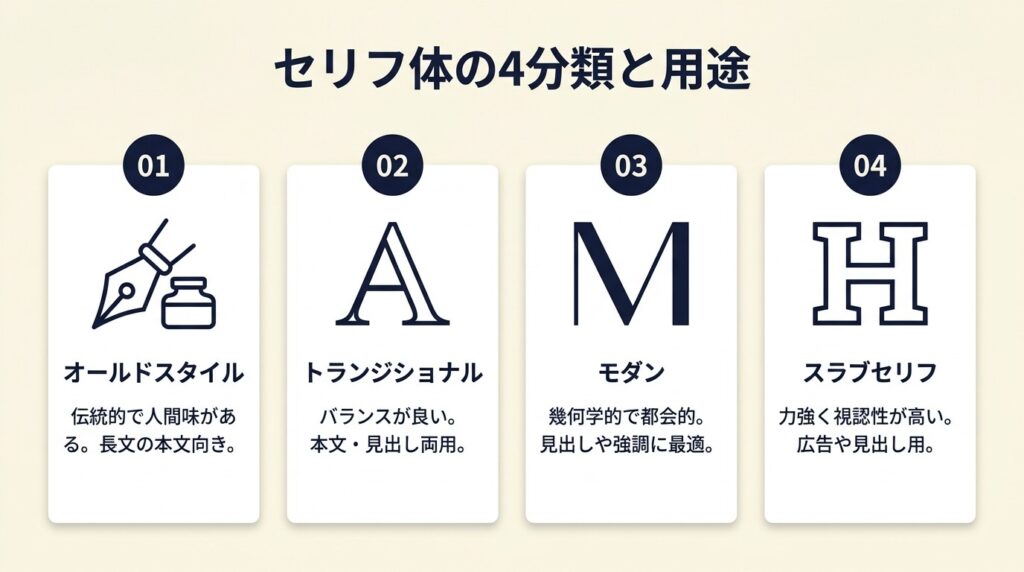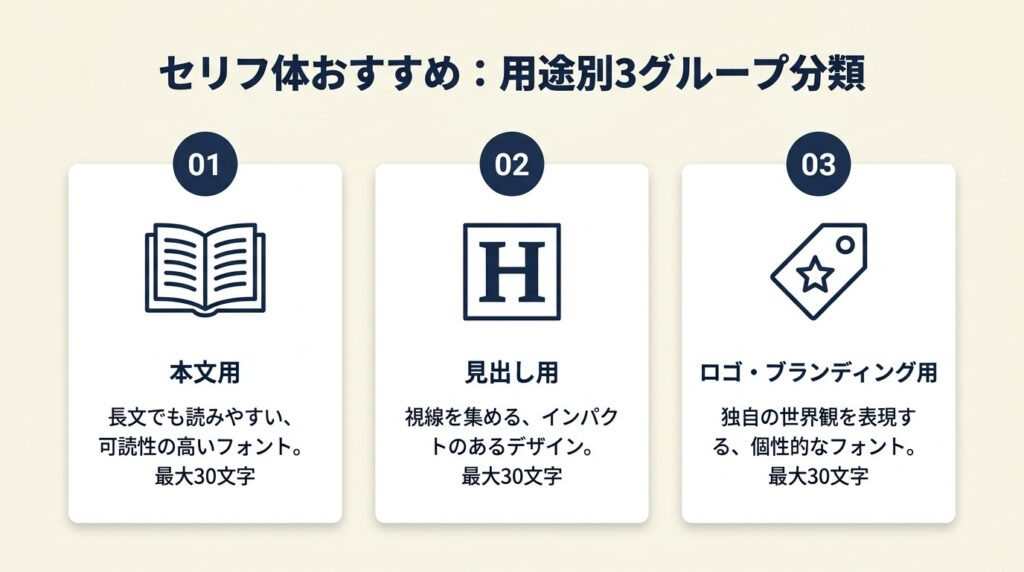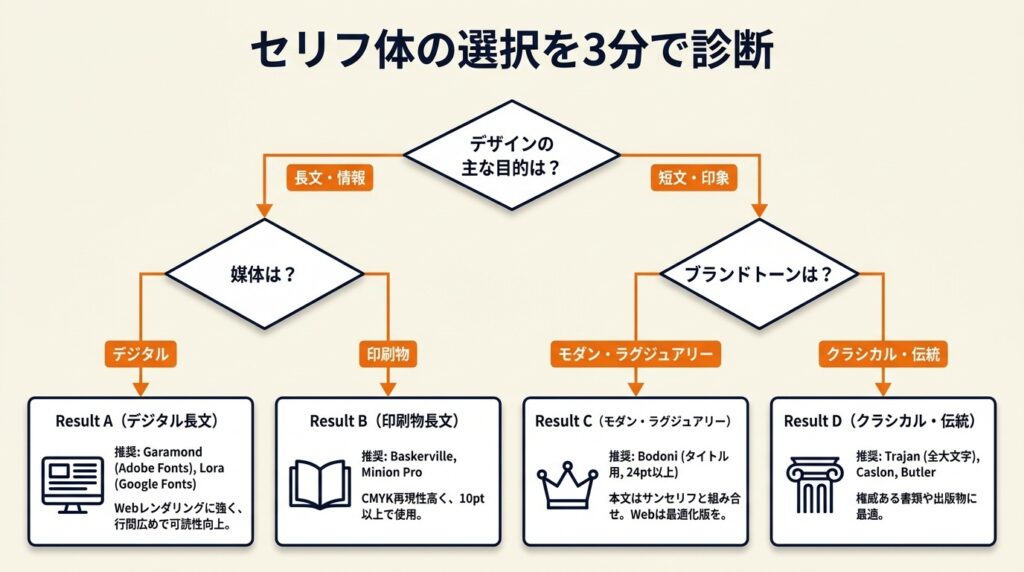
デザイナーが実務で使えるセリフ体は、用途別に選ぶと失敗がなく、見出しには10フォント中3選に絞れます。Adobe FontsとGoogle Fontsで無料商用利用できるものを中心に、本文・見出し・ロゴ別の選び方をこの記事で解説します。
本文用セリフ体はGaramondとBaskervilleの2択で9割の案件に対応できます。見出し・ロゴ用途ではBodoni・Trajan・Butlerが実務定番で、商用無料のものだけに絞っても選択肢は十分にあります。4種類の分類を理解するだけで、フォント選びに迷う時間を5分以内に短縮できます。
セリフ体の選択は「用途と印象の一致」が最優先です。見出しにはTrajanやBodoni、本文にはGaramondやBaskerville、モダン印象を出したい場合はスラブセリフのRockwellが定石です。初心者はGaramond一択から始め、次にBaskerville・Bodoniと段階的に習得すると迷いがなくなります。
セリフ体は4種類で用途が変わる
セリフ体は種類を理解すると選択肢が一気に絞られます。「なんとなく雰囲気が合いそう」でフォントを選んでいると、後工程で差し替えが発生しやすくなります。4分類を先に把握してから候補を絞るのが最速のアプローチです。
ブラケットセリフは長文可読性が最高
ブラケットセリフは、セリフ部分が滑らかなカーブで本体の線とつながっている書体です。GaramondやBaskervilleが代表例で、目が文字の流れを自然に追いやすい構造になっています。書籍・雑誌・Webの長文本文で最も多用されるのがこのタイプです。「読ませるデザイン」を作るなら、まずブラケットセリフを検討するのが最速の判断です。
ヘアラインセリフは高級感と繊細さを両立
ヘアラインセリフは、セリフ部分が水平方向に極細い線として表現された書体です。DidotやBodoniが該当し、縦の太線と横の極細線のコントラストが最大化されているため、ラグジュアリーブランドや高級誌での使用率が突出しています。ただし小サイズでは横線がつぶれやすく、12pt未満での使用は視認性が低下するため、見出しやロゴ専用と考えるのが正解です。
スラブセリフはモダンとクラシカルを両立
スラブセリフは、セリフ部分が角張った太い矩形形状の書体です。RockwellやUnit Slabが代表例で、太さのコントラストが低いため、アイキャッチやポスターで力強い印象を与えます。モダンデザインでありながら古典的な重厚感も持つため、テック系企業のブランディングから印刷物まで幅広く対応できます。「クラシカルすぎず、でも個性が欲しい」という状況で選ぶべきタイプです。
オールドスタイルは歴史的権威と読みやすさを両立
オールドスタイルは、15〜16世紀のヴェネチア・ローマン活版印刷に起源を持つ書体群です。Garamondがその代表で、縦横のストロークのコントラストが控えめで、長時間読んでも目が疲れにくい設計になっています。Times New Romanもこのカテゴリに分類され、新聞・学術誌・法律文書での採用実績が最も長い書体群です。権威性や信頼感を前面に出したいデザインで第一選択になります。
よくある質問
Q: セリフ体と明朝体は同じですか?
A: はい、同じ概念の別呼称です。セリフ体は欧文フォントの分類名で、日本語フォントでは同様の装飾を持つものを明朝体と呼びます。欧文デザインではセリフ体、和文デザインでは明朝体という用語が一般的です。
Q: サンセリフ体との使い分けはどう考えますか?
A: セリフ体は「伝統・権威・可読性」、サンセリフ体は「現代・清潔・視認性」と整理すると使い分けがしやすくなります。同一デザイン内でセリフ体を本文、サンセリフ体を見出しに使う組み合わせは実務でも多用されます。
セリフ体おすすめは用途で3グループに分類
用途で3グループに分けると選択肢が明確になります。定番フォントを調べると10種類以上出てきますが、「本文用」「見出し用」「ロゴ・ブランディング用」の3軸で整理すると候補を一気に絞り込めます。
見出し用セリフ体は3選が実務定番
見出し用に最も多用されるセリフ体はTrajan、Bodoni、Didotの3つです。
TrajanはAdobe Systemsのキャロル・トゥオンブリーが1989年にデザインした書体で、大文字のみのキャピタル設計を持ち、映画タイトルやポスターへの採用実績が豊富です。シャープな彫刻的フォルムが視線を集め、権威あるタイトルデザインに適しています。Bodoniは縦横ストロークの最大コントラストが特徴で、ファッション誌の表紙での採用率が高く、モダンラグジュアリーの代名詞的存在です。DidotもBodoniと同様のモダンセリフ系ですが、よりスタイリッシュで細身の印象を与えます。いずれも小サイズでの使用は非推奨で、24pt以上での使用が前提です。無料英語フォントを3ステップで即使える方法でも解説しているように、フォントの種類と用途の対応を最初に整理することが、選択ミスを防ぐ最短ルートです。
本文用セリフ体は可読性で2選に絞れる
長文本文で最も信頼性が高いのはGaramondとBaskervilleです。
Garamondは16世紀のフランス活字師クロード・ガラモン(Claude Garamond)の書体を原典とし、現在Adobe Fontsで無料商用利用が可能です。字間のリズムが均一で長時間読んでも疲れにくく、書籍・Webの本文フォントとして選ばれ続けています。デザイナーがお気に入り欧文フォントを解説した記事では「セリフ体からは王道のGaramond、古典的でモダンなBaskervilleをご紹介。個性が強めなものを好むデザイナー視点。」と紹介されています。
BaskervilleはGaramondより縦横のコントラストがやや強く、学術的・フォーマルな印象が加わります。18世紀イギリスの活版印刷業者ジョン・バスカーヴィル(John Baskerville)の設計を受け継いだ書体で、現代のスクリーン表示にも十分対応しています。Garamondで少し軽すぎると感じた案件でBaskervilleに変えると重厚感がちょうど整うケースが多いです。
ロゴ・ブランディング用は個性と汎用性で選ぶ
ロゴ・ブランディング用途ではButlerとMinion Proが実績豊富です。ButlerはFabian De Smet氏が設計したフリーフォントで複数ウェイト展開があり、骨格がしっかりしており小サイズでも視認性を保ちます。Minion ProはAdobe FontsでAdobe CC契約者が無料で使えるフォントで、豊富なウェイトと幅のバリエーションから微細なブランドトーン調整が可能です。ロゴ制作で1つ選ぶならMinion Proが最初の候補になります。日本語フォント無料おすすめ12選でも触れているように、ウェイトバリエーションの豊富さはフォント選びの重要な判断基準のひとつです。
よくある質問
Q: Times New Romanは商用利用できますか?
A: WindowsおよびmacOSにプリインストールされているTimes New Romanは、OSにバンドルされたライセンスの範囲内でのみ使用可能です。Web埋め込みや印刷物の商業利用では、Adobe FontsのTimes New Roman互換フォントや、完全商用フリーのIM Fell Englishなどを使用してください。
Q: Google Fontsで使えるセリフ体はありますか?
A: はい、あります。Google FontsにはLora、Merriweather、Playfair Displayなど複数の高品質なセリフ体フォントがあります。いずれも無料で商用利用可能で、Webフォントとして直接埋め込むことも可能です。
セリフ体の選択を3分で診断
以下の質問で用途に合うフォントタイプが3分で絞り込めます。Q1から順に答えてください。
Q1: デザインの主な目的はどちらですか?
長文・情報を読ませる場合はQ2へ、短文・ブランド印象を伝える場合はQ3へ進んでください。
Q2: 媒体はデジタル(Web・アプリ)ですか、印刷物ですか?
デジタルの場合は**Result Aへ、印刷物の場合はResult B**へ進んでください。
Q3: ブランドトーンはどちらに近いですか?
モダン・ラグジュアリーの場合は**
Result Cへ、クラシカル・伝統の場合はResult D**へ進んでください。
**
Result A(デジタル長文)**: Garamond(Adobe Fonts無料)を12pt以上で使用してください。WebフォントとしてGoogle FontsのLoraも代替可能です。GaramondはWebレンダリングでも字間の均一性が高く、画面読了率が維持しやすいフォントです。行間は文字サイズの1.7〜2.0倍に設定することで可読性が最大化されます。
**
Result B(印刷物長文)**: Baskerville(Adobe Fonts無料)を本文10pt以上で使用してください。版面が狭い場合はMinion Proでウェイトを細調整できます。BaskervilleはCMYK印刷での再現性が高く、インクのにじみが出ても字形の判別がしやすい設計です。10pt以下ではセリフ部分がつぶれるため使用しないでください。
**
Result C(モダン・ラグジュアリー)**: Bodoniをタイトルに使用し、本文はサンセリフ体(Helveticaなど)と組み合わせてください。24pt以上を厳守します。Bodoniの縦横コントラストは印刷時に最大限発揮されます。スクリーン表示では細い横線がアンチエイリアスで劣化するため、Webのみの媒体ではBodoni Moda等のスクリーン最適化版を選んでください。
Q: 日本語と欧文セリフ体を組み合わせる方法を教えてください。
A: 欧文セリフ体と日本語明朝体を組み合わせる場合、骨格の太さ・コントラスト・ウェイト感を揃えることが重要です。GaramondとヒラギノSerif、BaskervilleとA-CID明朝の組み合わせは実務での採用例が多いです。具体的には欧文フォントのCSSを先に指定し、Unicodeの範囲外(U+3040〜U+9FFF等)を日本語フォントで補完するfont-familyの記述順で対応します(デザインポケット セリフ体・明朝体組み合わせガイド)。